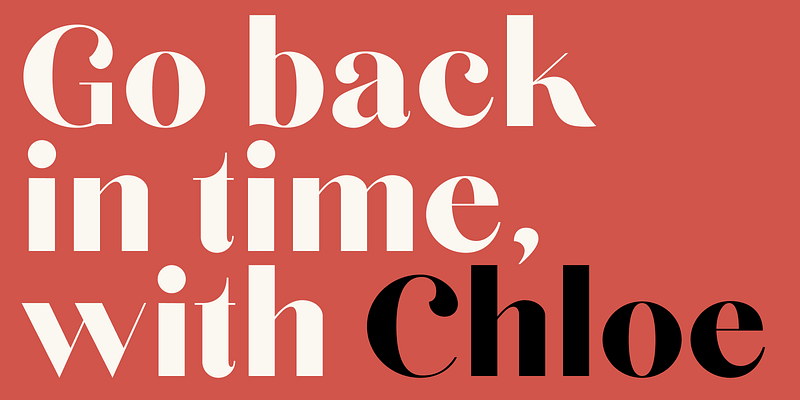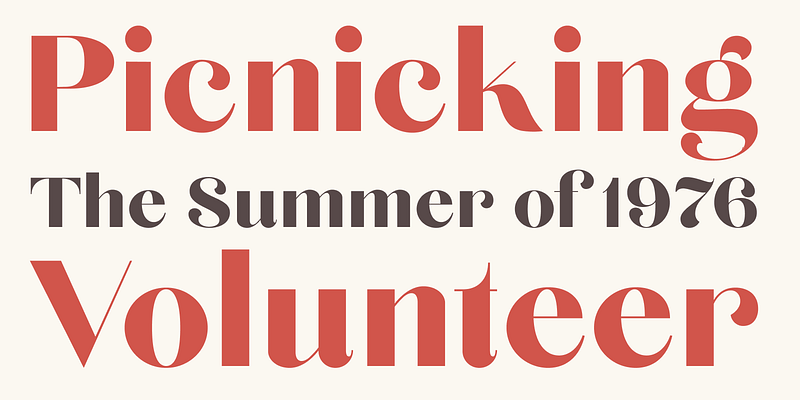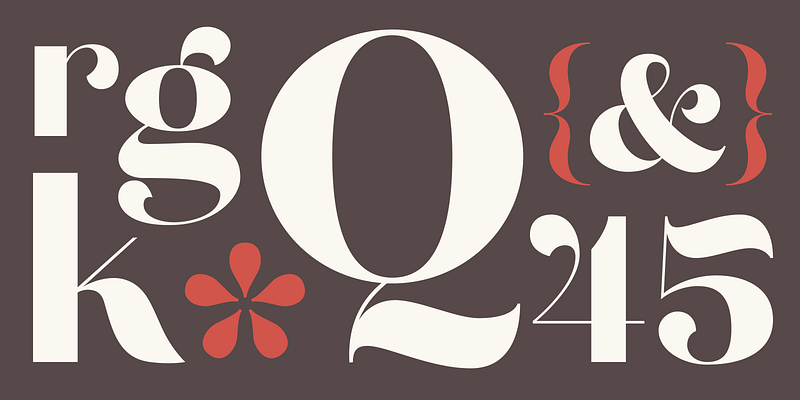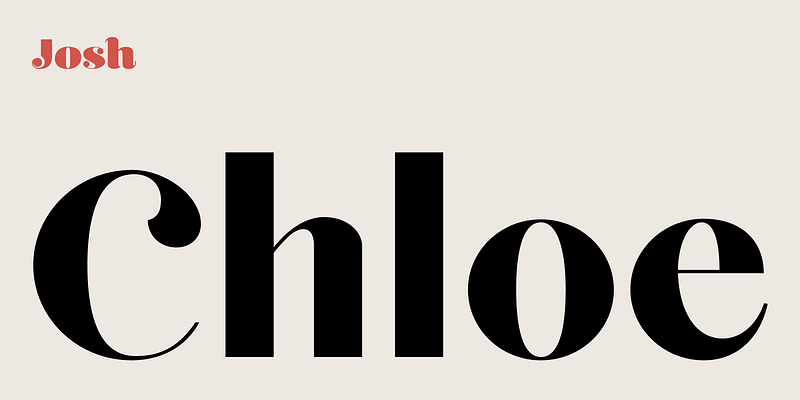
Chloe es una sans serif de alto contraste con detalles frívolos y alegres. Crea titulares llamativos y magníficos y diseños tipográficos elegantes con un toque vintage. Sus líneas contrastantes y terminales curvas aportan un aspecto vibrante y elegante a logotipos, tarjetas navideñas, invitaciones de boda, citas, anuncios y mucho más. Aunque se trata de un estilo único, es una tipografía versátil y llena de carácter, a la que volverás una y otra vez. Crea algo hermoso hoy mismo con Chloe.